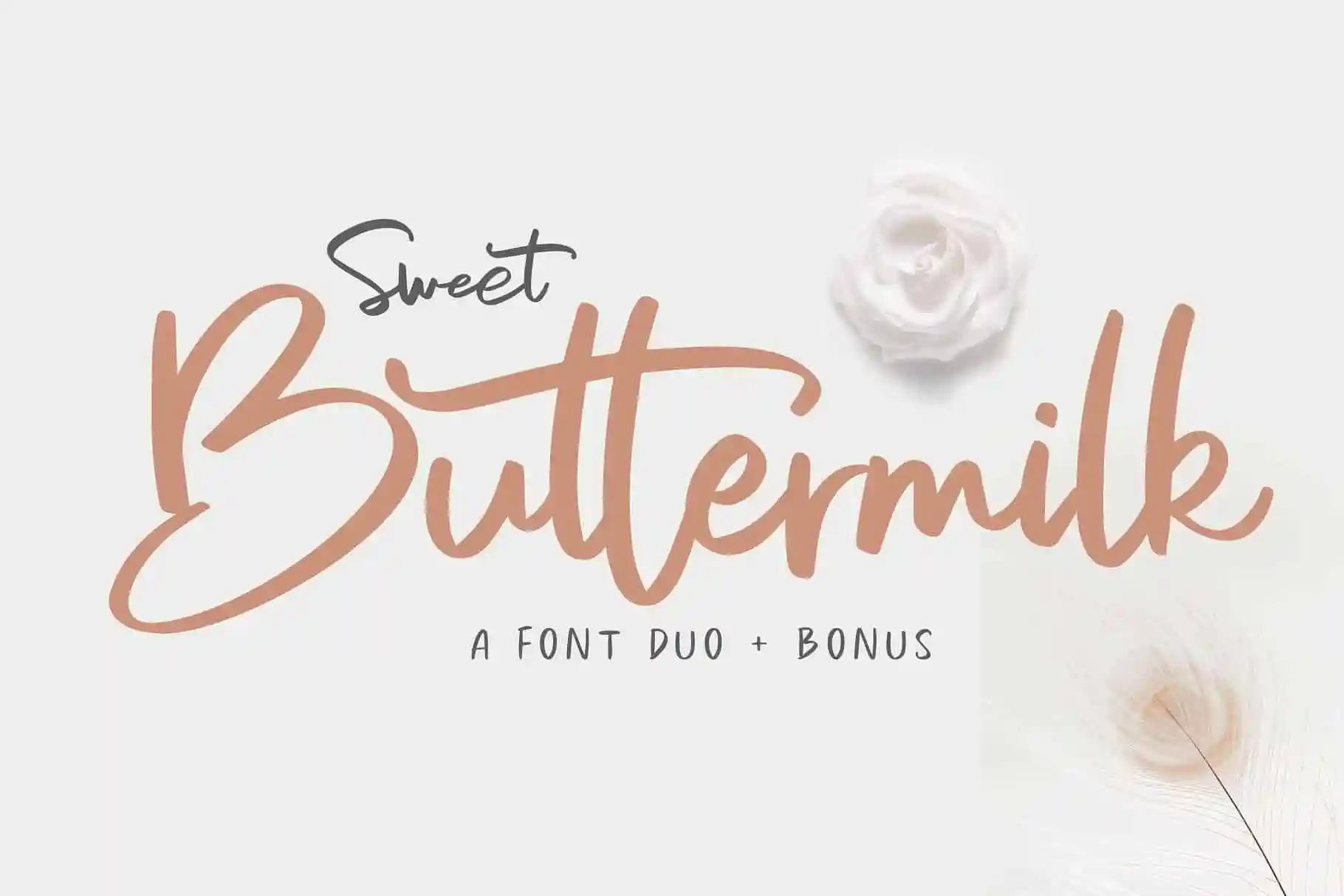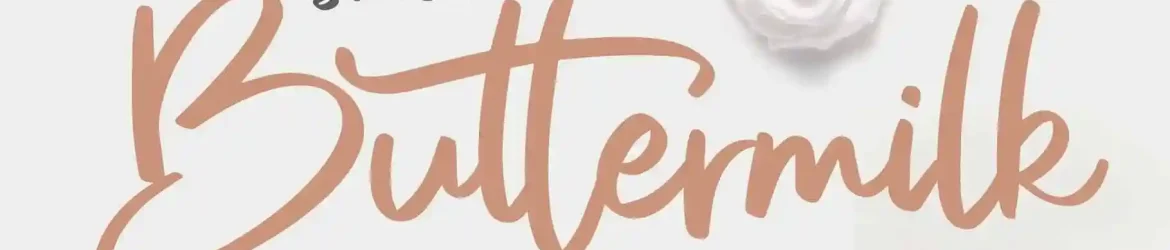
Sweet Buttermilk Font Duo – Download Grátis
A Sweet Buttermilk Font Duo é uma deliciosa dupla de fuentes script e sans-serif projetadas para contrastar e complementar-se com elegância e modernidade. Introduzimos a Sweet Buttermilk, criada pela Craft Supply Co., que se baseia na expressão da escrita manual real. Esta fonte script handwritten transforma o tipo em um trabalho de arte emocionante e bonito. Com sua aparência irregular e letra pintada, adiciona uma verdadeira impressão humana a qualquer projeto e vem acompanhada de muitos detalhes amorosos. Combine todas as estilos da font com a maneira como você desejar, adicione alguns swashes ornamentais ou bandejas ainda que apenas um único palavra se torne majestosa. A Sweet Buttermilk é uma combinação perfeita para designers apaixonados em criar designs únicos e emocionantes.